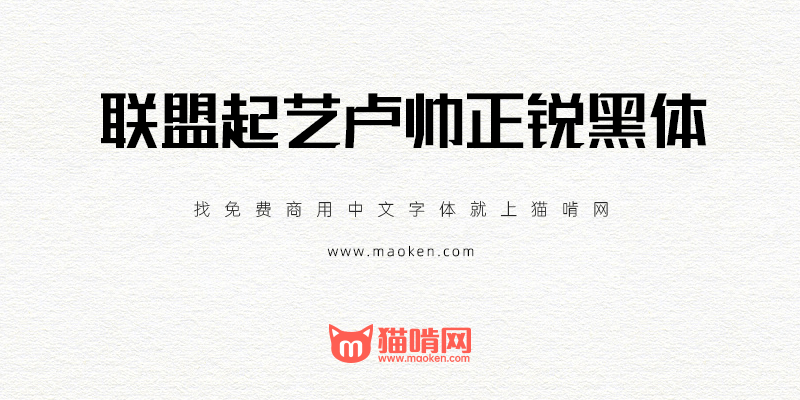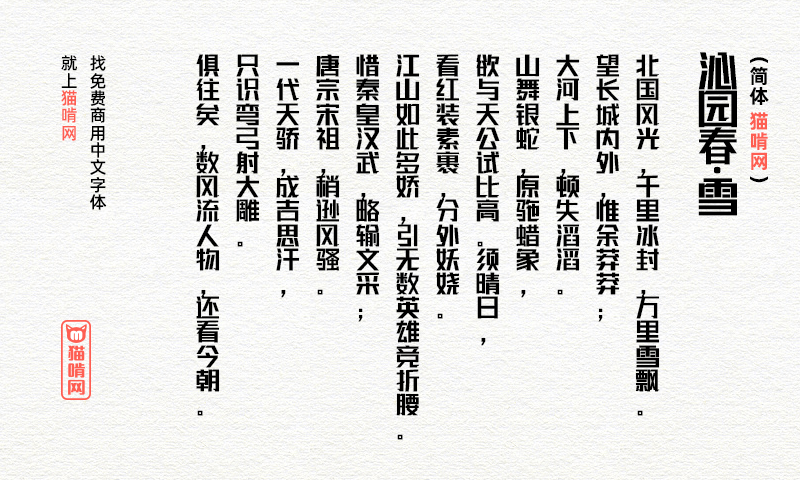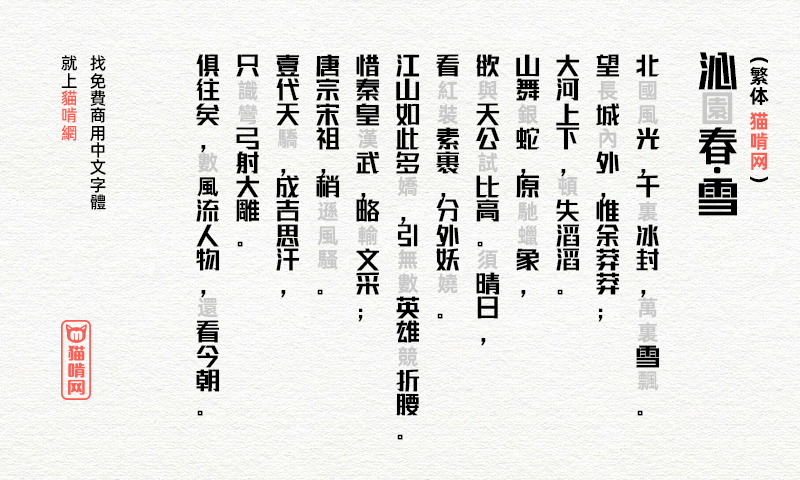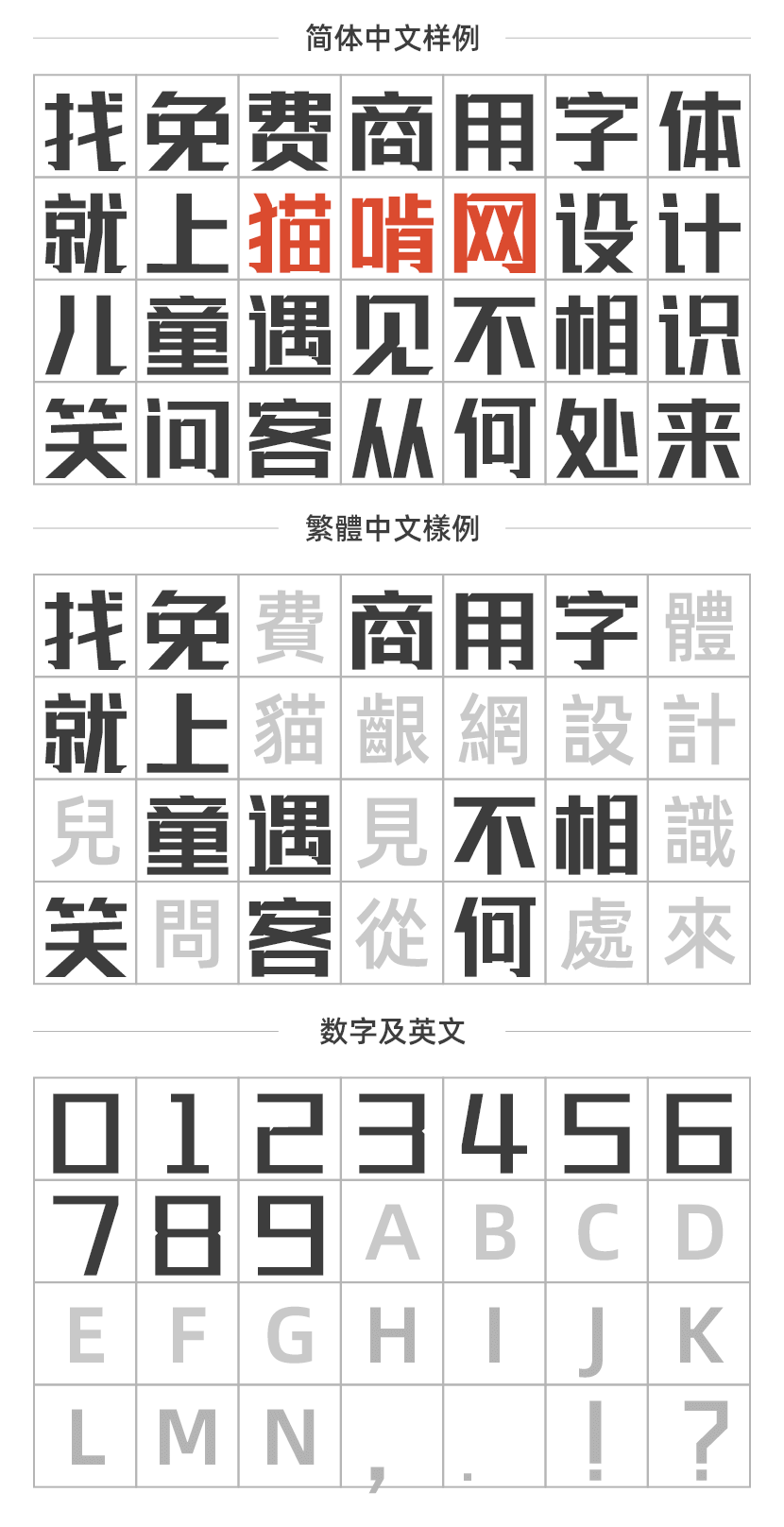
联盟起艺卢帅正锐黑体:将你的喜欢变成全新的字
你喜欢花,喜山川,喜平壤
你的喜欢就像一行诗
却没有具象的,属于它的文字
星辰更换,日月交替
历时半载,
现在,将你的喜欢
变成每一个全新的字
带到你身边
——
联盟起义卢帅正锐黑体正式发布,共计8000余字
——
一款免费字体并不能改变世界什么,但希望我们的努力,能让“初心”重新回归到我们自己心中正确的位置。
我们希望带给刚步入设计行业为字体版权头痛的你,正在设计行业沉沦为字体版权踟蹰的你,喜欢美好热爱生活的你,带来一次小小的感动。
联盟起艺卢帅正锐黑体这个字体的列宽有点问题,经过测试发现一些字的间距不一样。
殖 这个字,是错的,告知作者
• 确实少了一横
在CDR中 字体间距不一样
• 这款字体确实有问题,其他软件中还正常,独独在CDR中字距超宽还不一样
• 所以一直没用,不知道为啥字间距差那么多
字体间距不一样怎么回事?